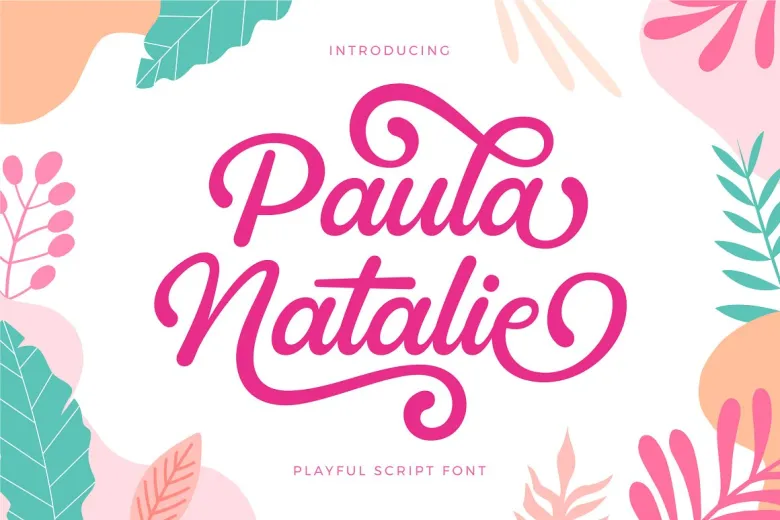
Font SVN Paula Natalie Download
Font SVN Paula Natalie là một font chữ thuộc bộ font SVN, đây là lựa chọn hoàn hảo cho những ai yêu thích sự thanh lịch và tinh tế trong thiết kế. Với nét chữ mềm mại, uốn lượn nhưng không kém phần rõ ràng, font chữ này mang lại cảm giác hiện đại và chuyên nghiệp, phù hợp cho nhiều dự án thiết kế từ thiệp mời, logo, đến website. Đặc biệt, Font SVN Paula Natalie còn nổi bật với khả năng tạo điểm nhấn trong từng chi tiết nhỏ, giúp bản thiết kế của bạn trở nên cuốn hút và ấn tượng hơn.